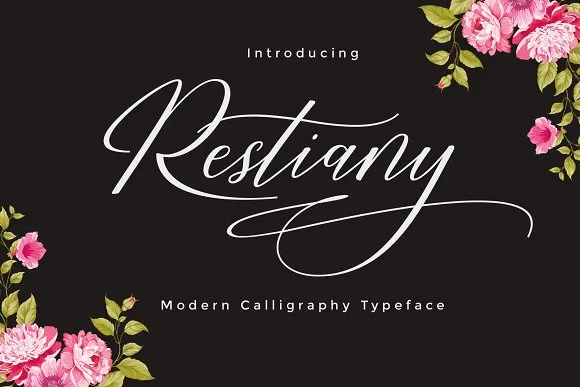
Descubra a Restiany Script Font, uma elegante e atrativa fonte de escrita cursiva projetada para designers apaixonados por novas ideias gráficas. Esta fonte moderna é perfeita para aqueles que desejam incorporar o estilo natural das letras manuscritas em seus designs digitais. Os traços deste font têm uma aparência suave e fluida, criando texturas elegantes e personalizadas. Ideal para criações como cartões de casamento, sinalização, títulos, logotipos, embalagens, marcação de produtos, a Restiany Script Font é uma escolha perfeita para designers que buscam equilíbrio entre casualidade e elegância. O design da fonte foi cuidadosamente elaborado pelo designer Hamilton de acordo com as diretrizes do Cooldesignlab, garantindo que seja fácil de usar e muito versátil em diferentes produtos gráficos. Se você está à procura de uma fonte para dar vida aos seus projetos, a Restiany Script Font é uma ótima opção.